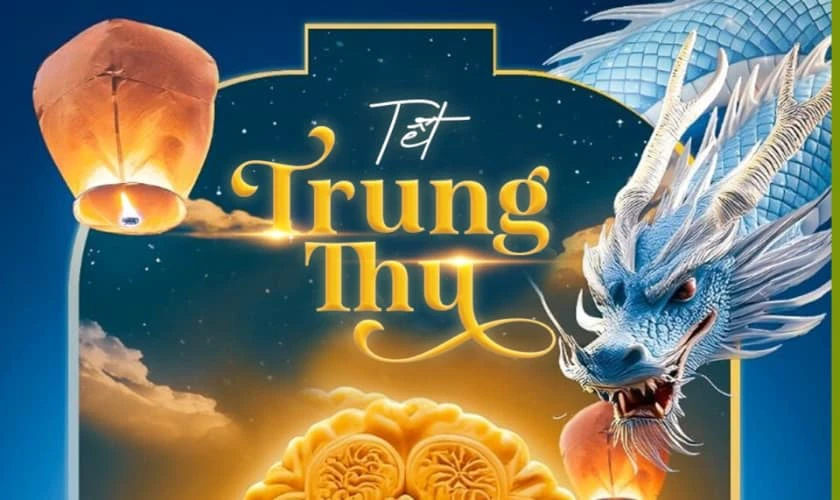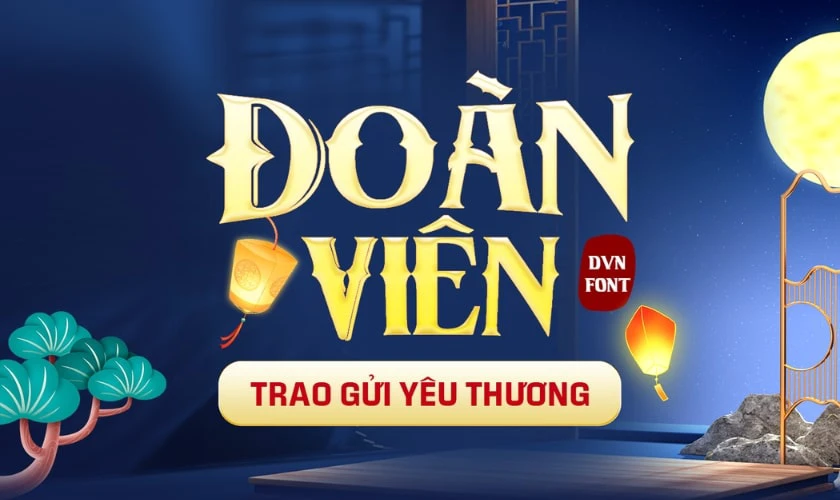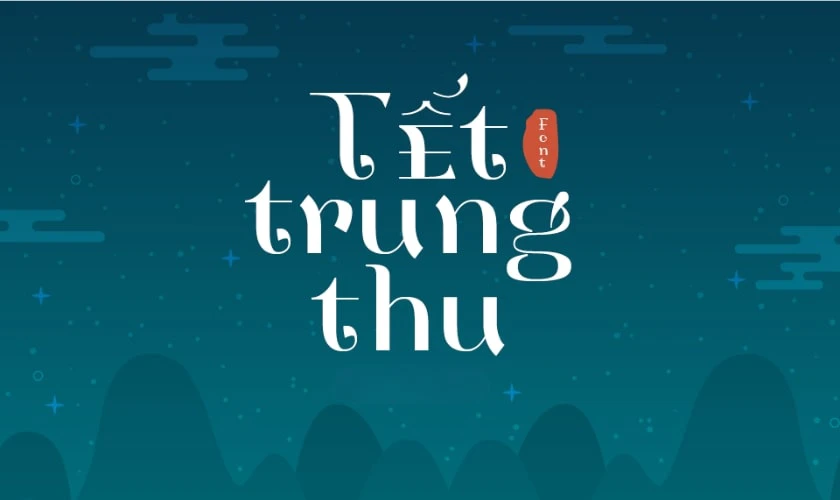
99+ Font chữ Trung thu Việt hóa, thư pháp, viết tay
Font chữ Trung thu Việt hóa được nhiều nhà thiết kế và người dùng yêu thích trong mùa lễ hội. Bộ sưu tập này mang đến sự đa dạng với nhiều phong cách như phông chữ vui Tết Trung thu dành cho poster, banner và ấn phẩm truyền thông. Bài viết sẽ gợi ý ngay các font trung thu Việt hóa miễn phí được chọn lọc chất lượng trên thị trường.
Font chữ Trung thu được xem là yếu tố quan trọng trong thiết kế ấn phẩm mùa lễ hội. Các font này mang nét truyền thống và tạo không khí ấm áp. Bạn có thể dùng font chữ Tết Trung thu thư pháp cho poster hoặc phông chữ vui Tết Trung thu trong thiệp. Hãy xem nội dung dưới đây để chọn font chữ trung thu đẹp nhất 2025.
Font Nuptial Liberty là một font chữ trung thu phổ biến với phong cách truyền thống đậm nét Á Đông. Font này được nhiều nhà thiết kế lựa chọn khi muốn tạo ra những mẫu poster, banner hay thiệp mời mang tinh thần lễ hội. Với đường nét uốn lượn mềm mại, font chữ Tết Trung thu này đặc biệt phù hợp trong các thiết kế có tính trang trí cao.
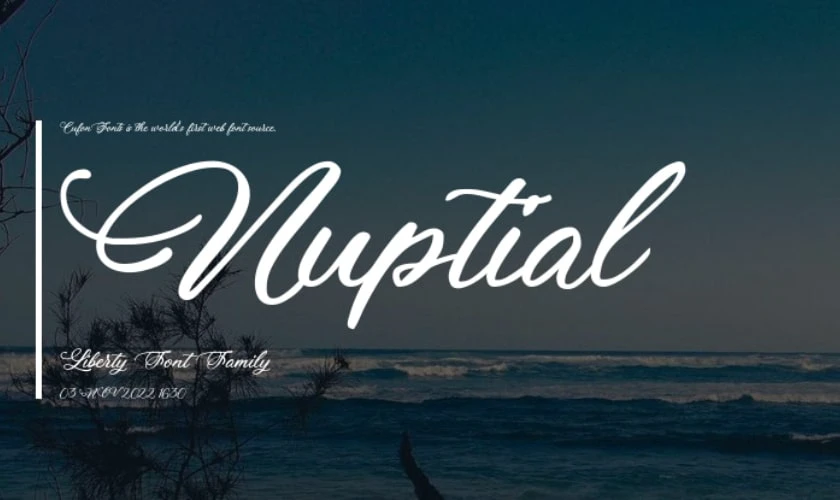
Người dùng dễ dàng áp dụng font trung thu Việt hóa này vì nó hỗ trợ đầy đủ dấu và ký tự tiếng Việt. Ngoài ra, phông chữ vui Tết Trung thu như font Nuptial Liberty còn tạo cảm giác gần gũi và mang đến sự tinh tế cho sản phẩm. Đây là một lựa chọn lý tưởng cho các dự án cá nhân và doanh nghiệp.
Font Hourglass Of Shine là font chữ trung thu được thiết kế theo phong cách thư pháp truyền thống. Font này giúp truyền tải trọn vẹn tinh thần lễ hội Trung thu và những giá trị văn hóa xưa. Đường nét của font khá thanh thoát nhưng vẫn giữ sự chắc chắn.
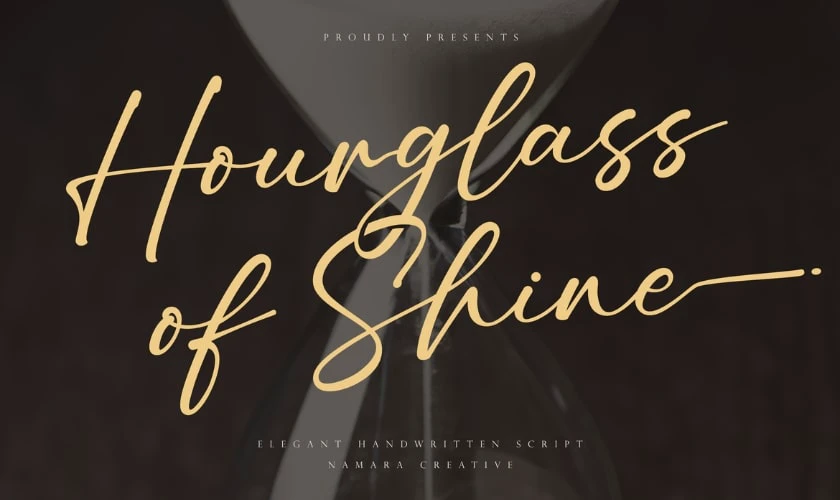
Khi sử dụng font chữ Tết Trung thu này, người dùng dễ dàng tạo ra ấn phẩm nghệ thuật từ thiệp chúc Tết Trung thu cho đến biển quảng cáo. Font trung thu Việt hóa này hỗ trợ đầy đủ tiếng Việt, phù hợp với nhu cầu thiết kế đa dạng.
Font UVN Bay Buom là font chữ trung thu việt hóa được nhiều bạn trẻ yêu thích. Với phong cách bay bổng, font này mang lại cảm giác vui tươi và hồn nhiên. Đặc biệt, font chữ Tết Trung thu này có đường nét mềm mại và dễ đọc. Người dùng có thể áp dụng font trung thu Việt hóa này cho thiệp mời, banner, standee hoặc ấn phẩm quảng cáo.
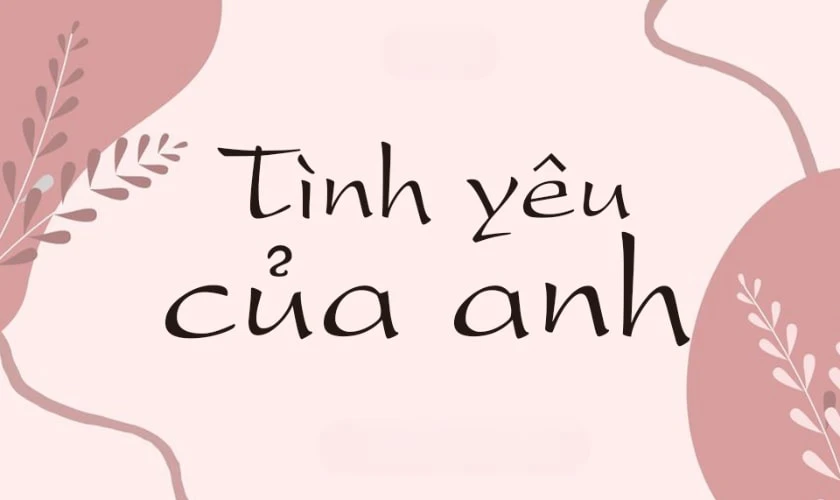
Với phông chữ vui Tết Trung thu này, thiết kế trở nên gần gũi và sinh động hơn. Đây là một font chữ phù hợp khi muốn tạo sự khác biệt cho sản phẩm mà vẫn giữ nét truyền thống.
Font Dear Script là font chữ trung thu quen thuộc với những ai yêu thích nghệ thuật chữ viết truyền thống. Font này mang đến cảm giác hoài niệm và trang trọng, phù hợp trong thiết kế poster, thư pháp điện tử và các ấn phẩm Trung thu. Font chữ Tết Trung thu này hỗ trợ tiếng Việt. Vì vậy người dùng có thể viết nội dung đầy đủ mà không gặp lỗi font.
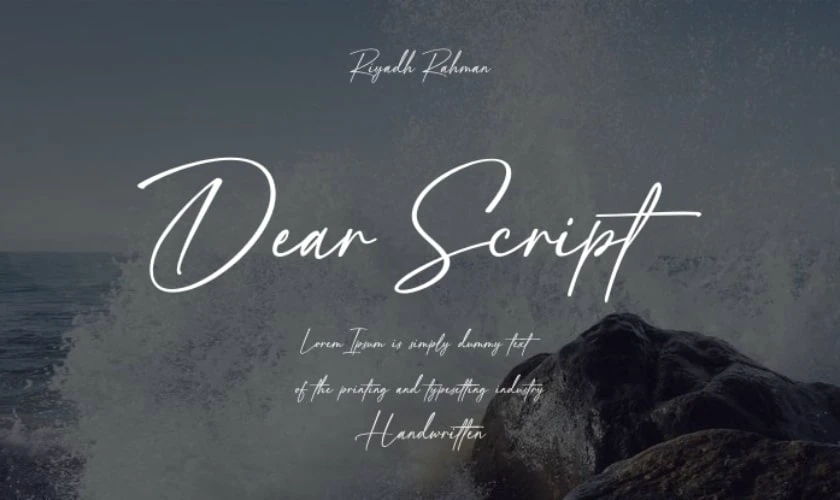
Với phông chữ vui Tết Trung thu như Dear Script, thiết kế của bạn sẽ vừa mang nét cổ điển vừa hiện đại. Đây là một font chữ trung thu việt hóa rất đáng để sử dụng trong mùa lễ hội.
Font Hoa Mùa Thu là font chữ trung thu có thiết kế cân đối, đường nét sắc sảo và tinh tế. Font này thích hợp với các sản phẩm quảng cáo, poster hoặc standee Trung thu. Người dùng có thể dễ dàng kết hợp font chữ Tết Trung thu này với các font khác để tạo điểm nhấn.
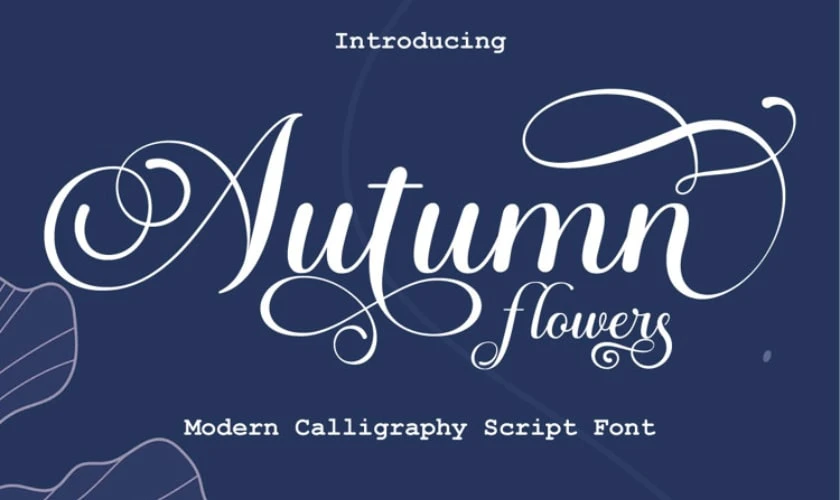
Với phiên bản font trung thu Việt hóa, người dùng sẽ không gặp khó khăn khi nhập nội dung tiếng Việt. Bên cạnh đó, phông chữ vui Tết Trung thu Hoa Mùa Thu còn được dùng rộng rãi trong thiết kế banner sự kiện và in ấn. Đây là một font chữ kết hợp tốt giữa thẩm mỹ và công năng.
DVN Dragon Việt hóa là một trong những font chữ trung thu được nhiều designer ưa chuộng. Font mang phong cách mạnh mẽ với nét chữ dày, thể hiện sự uy nghiêm và nổi bật. Các chi tiết của font gợi nhớ đến hình ảnh rồng Á Đông nên rất phù hợp với chủ đề truyền thống và lễ hội.
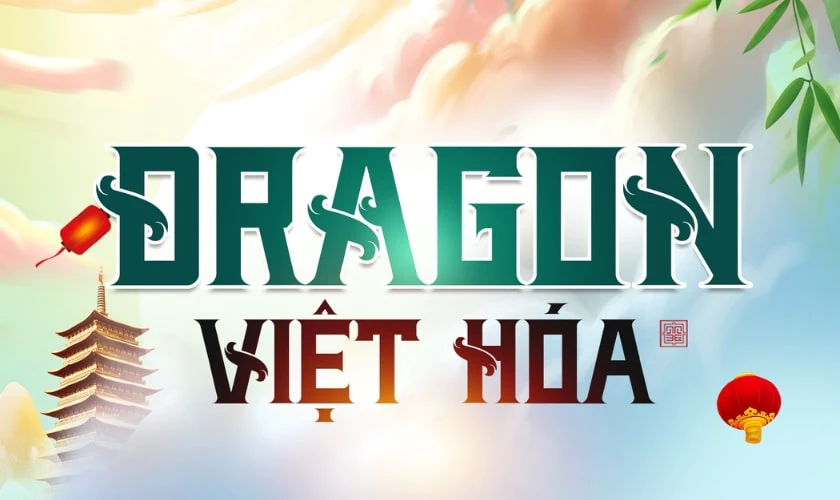
Đây là lựa chọn tốt cho các thiết kế thiệp chúc mừng, banner trung thu hay tiêu đề cần sự mạnh mẽ. DVN Dragon cũng được việt hóa đầy đủ dấu, giúp bạn dễ dàng sử dụng cho nội dung tiếng Việt. Với sự kết hợp hài hòa giữa nét đẹp truyền thống và hiện đại, font mang lại sức hút thị giác cao.
Font KD Mid Autumn là font chữ trung thu độc đáo, được thiết kế với phong cách gọn gàng và mạnh mẽ. Font này thích hợp cho các poster, thiệp hoặc ấn phẩm cần sự rõ ràng. Font chữ Tết Trung thu như KD Mid Autumn tuy đơn giản nhưng lại mang sức hút đặc biệt.
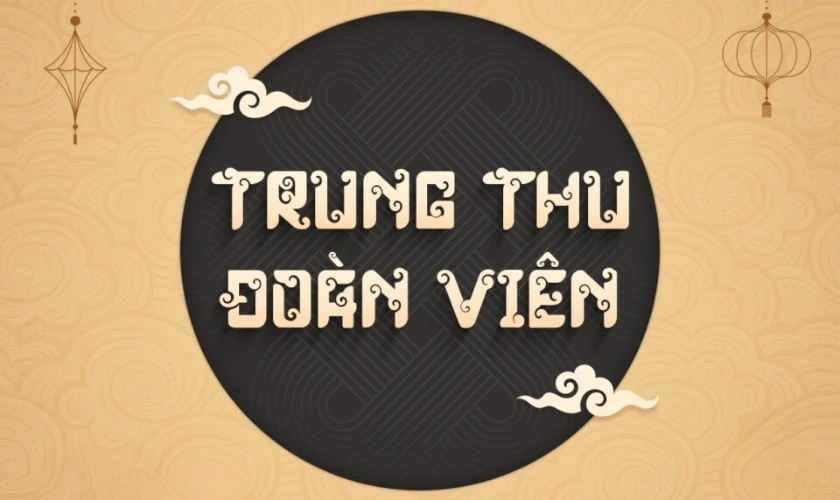
Font trung thu việt hóa này giúp hiển thị tiếng Việt đầy đủ và không gặp lỗi. Bên cạnh đó, phông chữ vui Tết Trung thu này cũng dễ kết hợp với hình ảnh, màu sắc trong thiết kế. Đây là font chữ mang lại sự tiện dụng và tính ứng dụng cao.